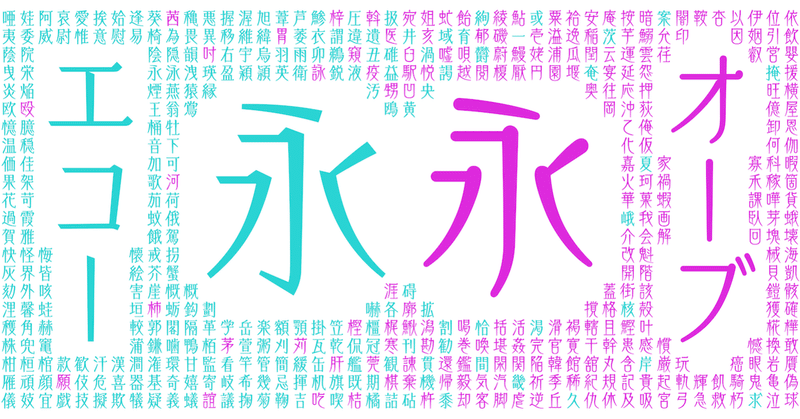
似ているけどよく見ると...? 洗練された長体な書体「エコー」と「オーブ」
今回ご紹介するのは「エコー」と「オーブ」という似て異なる特徴を持つデザイン書体です。後半で書体の特徴を活かしたおすすめの使い方も解説しますので、最後までお付き合いください!
1. フォントの特徴を言葉にしてみる
まずは「エコー」と「オーブ」の組見本をご覧ください。
品があって素敵な書体ですよね。ただこの2書体、どことなく似ているような...でも少し違うよな...そんな風に感じませんか?
一見、わずかに思えるデザインの工夫であっても、50音や漢字全体に、その工夫を反映させることで、その書体から受ける印象は大きく変わります。「エコー」と「オーブ」の特徴を細部の共通点と相違点からひとつずつ見ていくと、その謎が解けていきます。一緒に見ていきましょう!
・デザインの共通点
まずは「エコー」と「オーブ」の共通点から。
(1) 高い重心
重心とは文字における視覚的なバランスの中心にあたります。一般的には重心が高めであれば緊張感や品格を生み、低めなら安定感や親しみやすさを感じさせると言われています。「エコー」と「オーブ」を見てみると、重心が低い例よりも重心が高く設計されています。
この2書体から感じる品の良さは重心の設計が関係しているようですね。
(2) 長体なデザイン
ベーシックな和文書体は「UD新ゴ」のように正体(縦横の比率が同じ)でデザインされますが、「エコー」と「オーブ」は縦長なフォルムをしていますね。このような書体は “長体書体” や “コンデンス書体” と呼ばれています。
これらは主に、行の長さが限られる際などにより多くの文字情報を記載する目的で作られることが多いですが、その他にも縦長なフォルムにすることで、緊張感のあるスタイリッシュなニュアンスを表現できる、というデザイン的な特徴も持ち合わせています。
・デザインの相違点
続いて2書体のデザインの違いについて追っていきます。
(1) 骨格の違い
骨格とは文字の画線の芯にあたるものです。
かなの「ふ」から2書体を比較すると、「エコー」の骨格は直線的かつ水平垂直を意識させるデザインで、左右対称な構造で図形的なフォルムになっています。それに対し「オーブ」の骨格はわずかにたわみが見られます。また、手書きに由来する脈絡(筆の流れ)がデザインに取り入れられ、有機的な表情を持ちます。
(2) エレメントの違い
書体デザインの違いは、骨格以外にエレメントから判別することもできます。エレメントとは骨格を肉付けるパーツの形を意味し、書体を特徴付ける大きな要素のひとつです。
実際に画像で比較して観察すると「エコー」は始筆とウロコに四角いデザインを採用しています。一方「オーブ」はどちらも丸みのあるデザインになっていますね。
骨格とエレメント、デザインをそれぞれ緻密に設計することで、共通点を持ちながらも「エコー」はスッキリと引き締まった風合い、「オーブ」は柔和で優しく流麗な風合いに仕上がり、それぞれの書体の個性となっています。
2.文字組小噺 〜長体とプロポーショナルメトリクス〜
こちらの画像は「UD新ゴ」「エコー」「オーブ」の3書体を同じ文章で字間を調整せず文章を組んだもの(ベタ組み)です。
「UD新ゴ」は文字同士が隙間なく組まれているのに対し、「エコー」と「オーブ」の2書体には余裕があることが分かります。
ではこちらはどうでしょうか。「UD新ゴコンデンス70」は長体の書体ですが、先ほどの「エコー」と「オーブ」を比べて「UD新ゴコンデンス70」は隙間なく組まれています。
この違いは、書体の字幅の設計と関わりがあります。
・仮想ボディと文字の幅
一般的に和文書体をデザインするときは仮想ボディと呼ばれる正方形の枠の中に対して、同じ形を意識した比率で文字が設計されます。それが今回「エコー」と「オーブ」では正方形の仮想ボディに対して、約86%の縦長な比率で文字がデザインされています。
「UD新ゴコンデンス70」は仮想ボディも文字デザインも、縦長の形になっています。それに対し「エコー」と「オーブ」は仮想ボディが正方形のままで文字デザインは長体なのでベタ組をすると文字同士が一定の間隔をあけて並んでいます。
仮想ボディとは文字を打つときに目には見えない、透明な枠線のようなものといえますね。
「エコー」と「オーブ」の仮想ボディが正方形なのは全角でも使える長体のデザインを目指して設計されたからです。エレガントな雰囲気をもつ両書体を、ゆったりとした字間と合わせて使うことで、軽やかな空気感をプラスしています。文字間の余白も書体デザインの大切な要素なのです。
・プロポーショナルメトリクス
余白も含めて書体デザイン...というのはわかったけど、「UD新ゴコンデンス70」のように、タイトな字間で⽂章を組めたらいいのに...と思った皆さん、実は「エコー」と「オーブ」も「UD新ゴコンデンス70」のように、仮想ボディ自体を長方形にして文章を組むこともできます!
プロポーショナルメトリクスとは、フォント情報の中にあらかじめ搭載されている文字詰め機能を指しています。実際に「エコー」と「オーブ」でベタ組みとプロポーショナルメトリクスを比較してみましょう。
これから「エコー」と「オーブ」を使用する際には、OpenType機能のプロポーショナルメトリクスを文字組の一つの方法として思い出していただけたら幸いです!
3. 書体開発からリリースまでの道のり
最後に2書体の開発秘話についてお話しします。
2018年にリリースした「エコー」と「オーブ」はモリサワタイプデザインコンペティション 2012で応募作品の一つだった「なでしこ」から誕生しました。
こちらがコンペティション後に調整された「なでしこ」の文字と、最終的に製品化された「エコー」と「オーブ」の文字です。
「なでしこ」は「エコー」が持つスクエアな骨格と、「オーブ」に見られる丸い先端やウロコを併せ持つ作風になっていますね。
ここから「エコー」は骨格もエレメントも四角い書体へ、「オーブ」は骨格もエレメントも丸い書体へとデザインが派生し、2書体になりました。
さらに「エコー」にはウエイト展開も加えられました。
形状がよりシンプルな「エコー」を汎用的にお使いいただけるよう、見出しや小見出しだけでなく、キャプションなどの短い文章も組めるようにL・R・Bのウエイト展開が誕生したのです。
デザインの派生からウエイト展開というように、今の「エコー」と「オーブ」に至るまで、このような変遷がありました。
これは余談ですが、街なかで「エコー」や「オーブ」がポスターや製品などで使われているのをみると、こういうテイストで親和性があるのか!といった風に意外な発見があり、大変興味深いです。これからも様々な使用事例に出会えたらいいなと思っています。
4. おわりに
今回は洗練された長体な書体「エコー」と「オーブ」について紹介してきました。フォントの個性の秘密は、デザインの工夫にありましたね。
今後気になるフォントを見つけた時、その特徴がどのようなものなのか、街中で心の虫眼鏡を構えて見てみるのはいかがでしょうか🔎
「エコー」と「オーブ」のもう一つの文字組方法、プロポーショナルメトリクスの活用もお忘れなく!
これからも書体の隠された秘密やフォントの良さについて皆さんと共有していくことができたらいいなと思います。